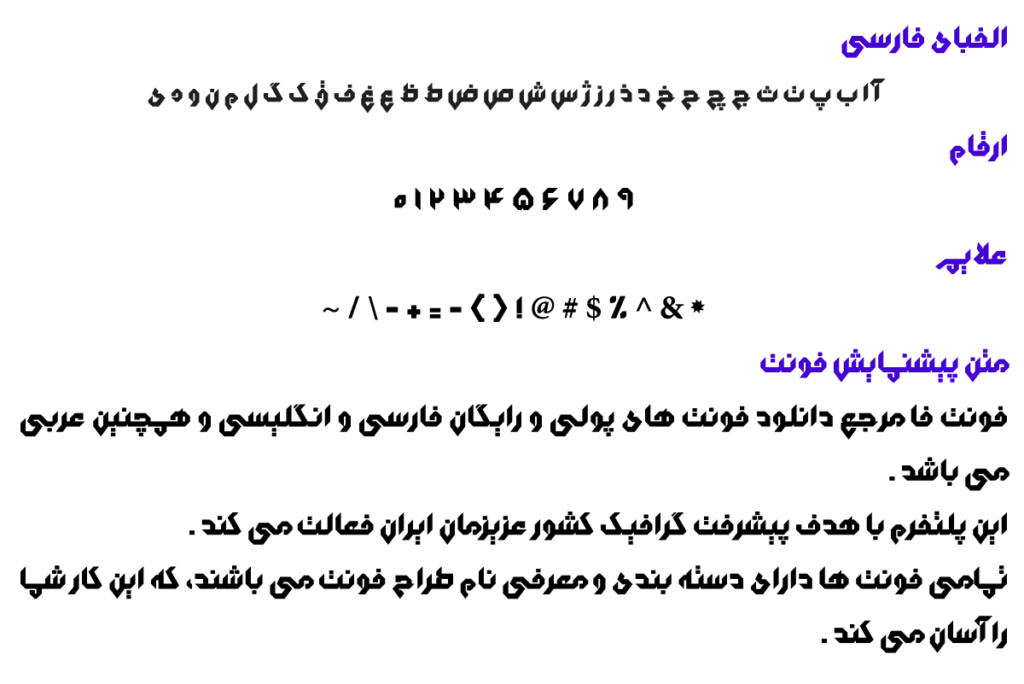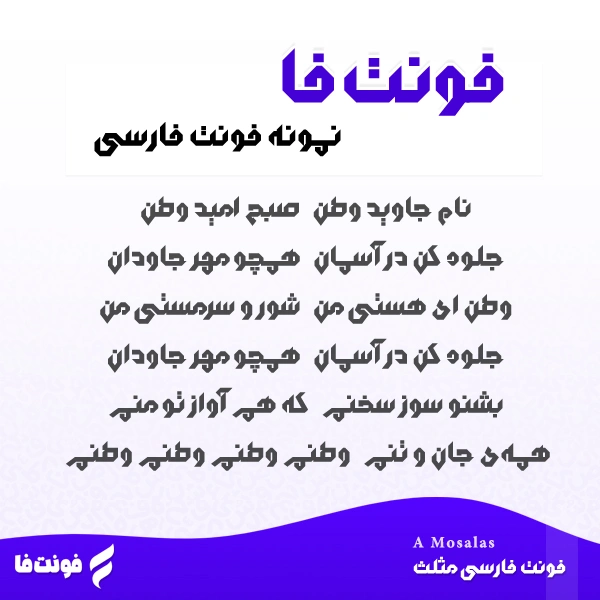
فونت فارسی مثلث – A Mosalas
سال ساخت فونت: 1393
طراح فونت: مجتبی کیا نوع فونت: فونت هندسی
توضیحات و معرفی فونت مثلث
فونت فارسی مثلث ( A Mosalas ) از مجموعه فونت های آزاد می باشد، و نیز نوع فونت هندسی می باشد.
فونت خوشگل مربوط توسط مجتبی کیا در سال 1393 طراحی و ساخته شده است.
و نیز فونت A Mosalas در یک وزن پر رنگ است.
نمونه ی تصویری زیر، تایپ فیس را در ترکیب با شعری میهن دوستانه نمایش میدهد.